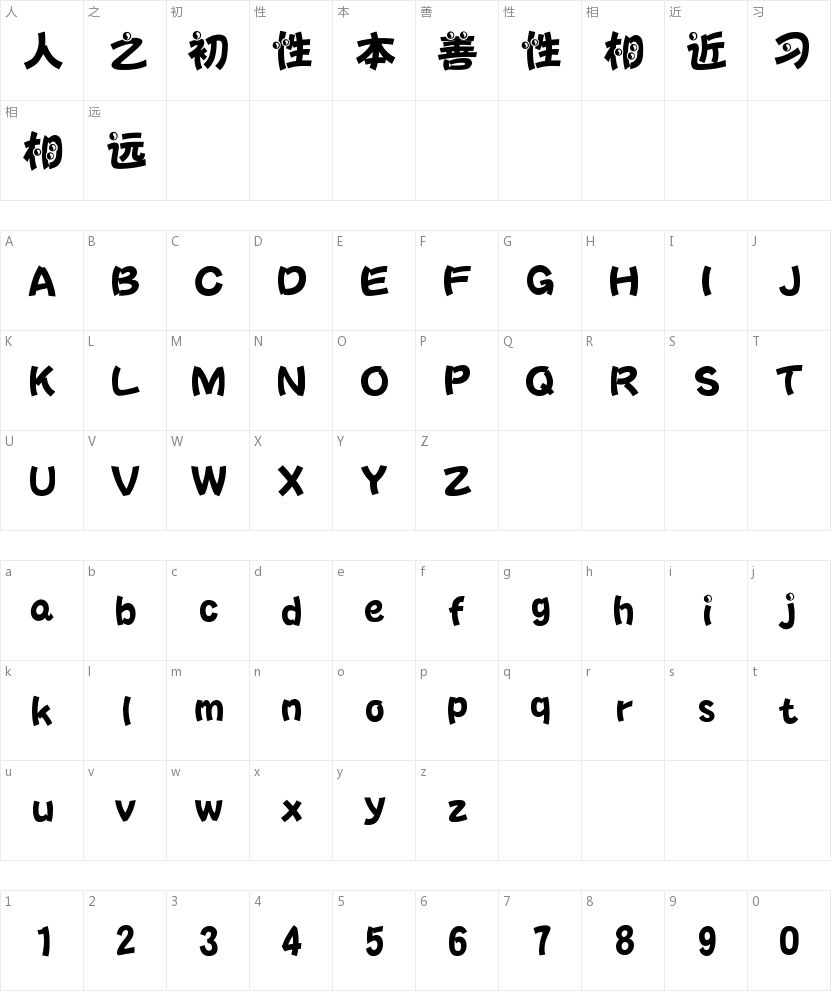
迷你简太极
迷你简太极是一款具有中国传统文化内涵的字体,以太极八卦图案为基础,融入现代化的字形设计,充分体现出中国传统文化的特色。这款字体采用简洁的笔画,拥有良好的可读性,可以用于各种设计中,比如标志、广告、网页等。
迷你简太极是一款非常不错的手写艺术字体,具有很好的视觉感,适合于文化类的宣传设计、商业类品牌的广告和产品包装设计以及个性化文字排版等较多场景。
迷你简太极字符映射图